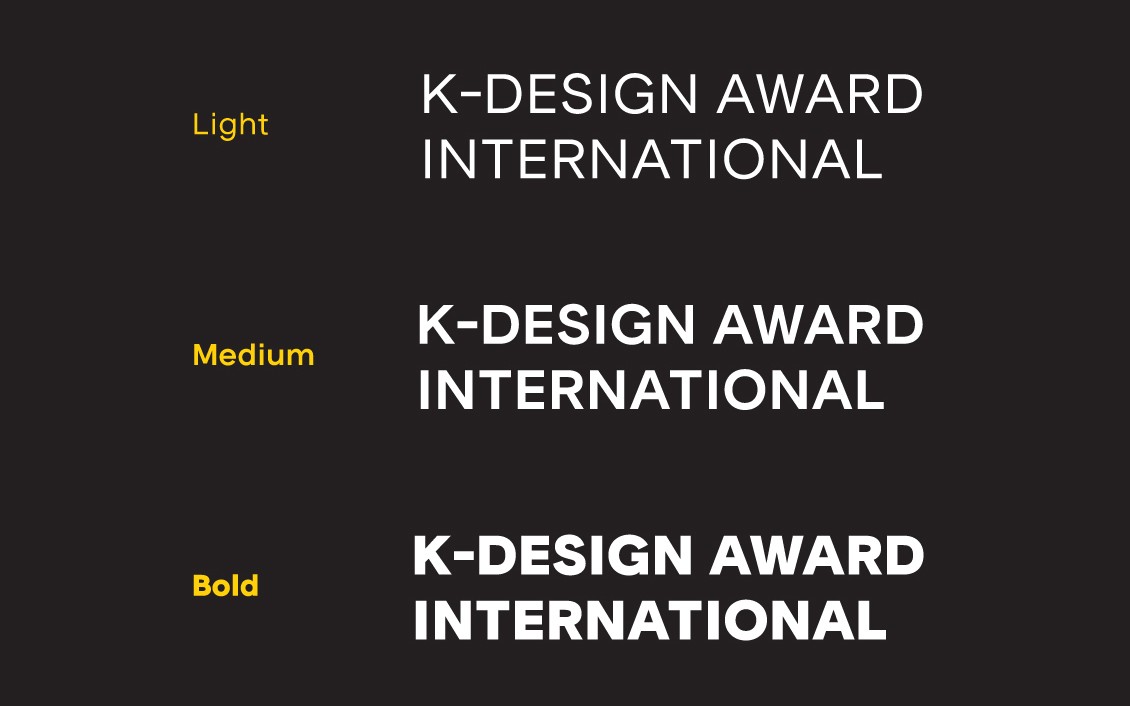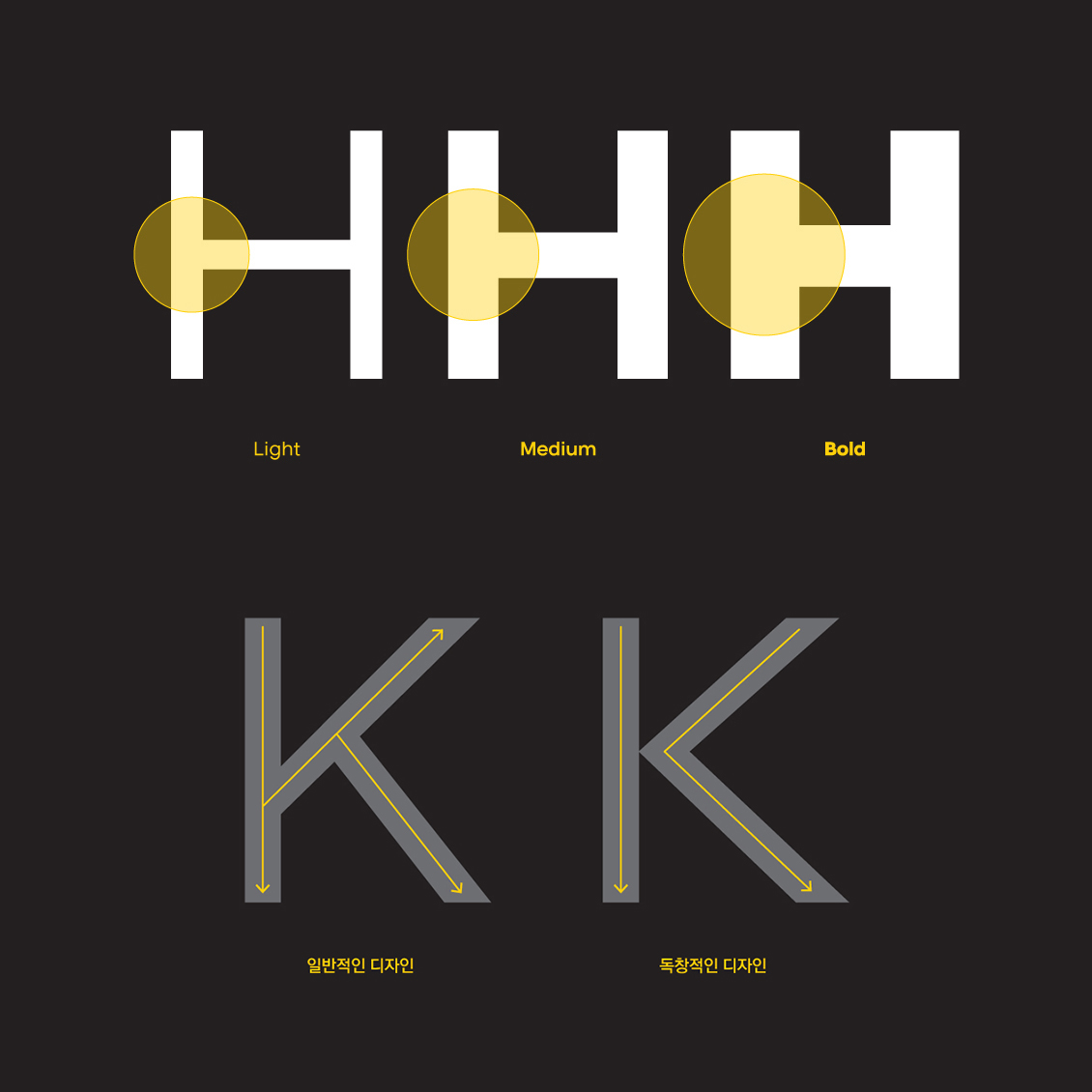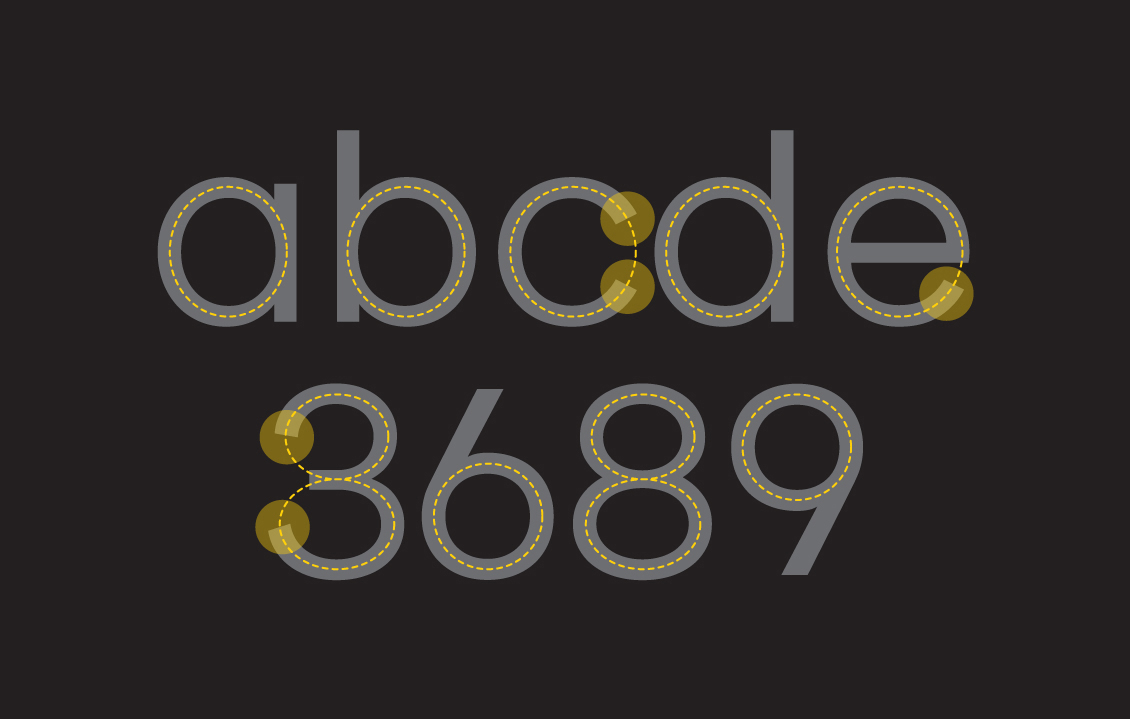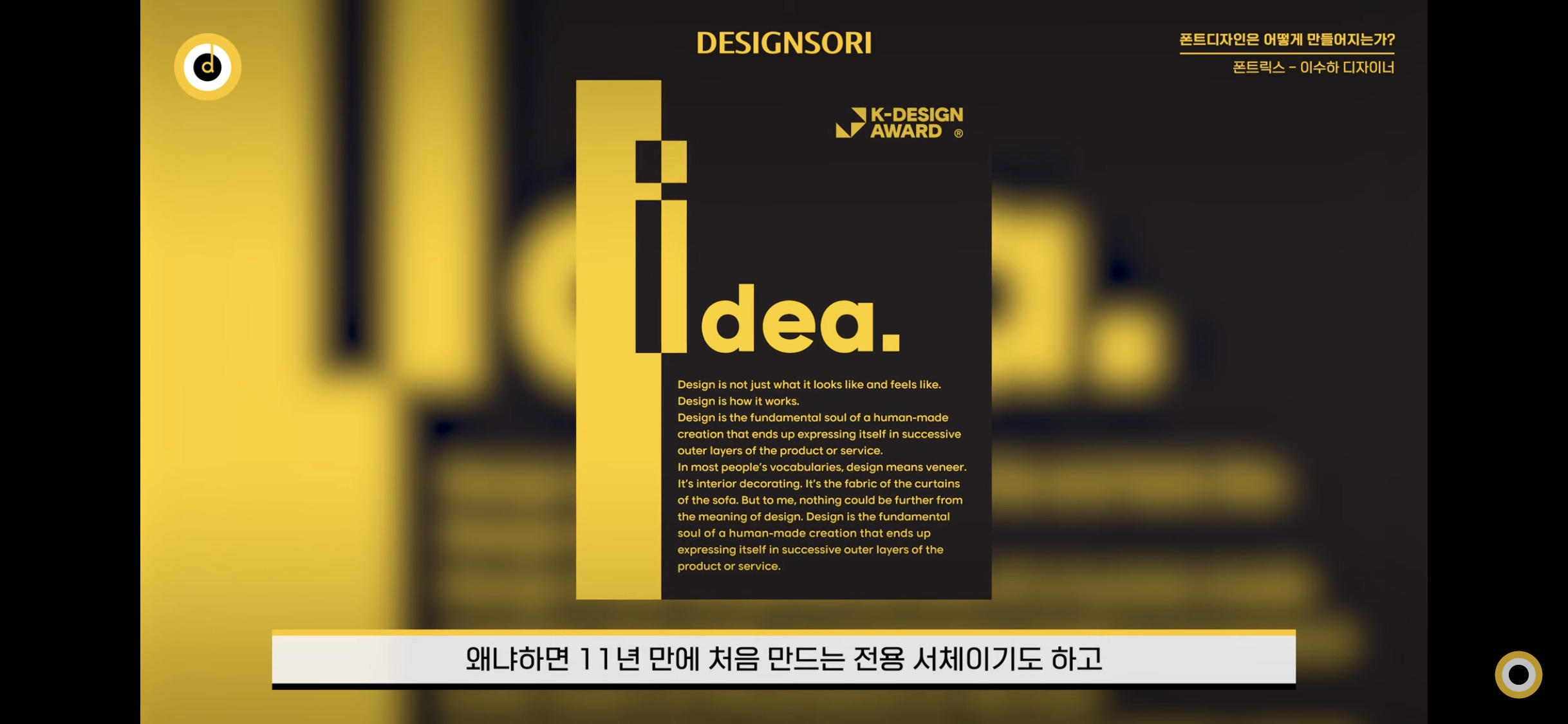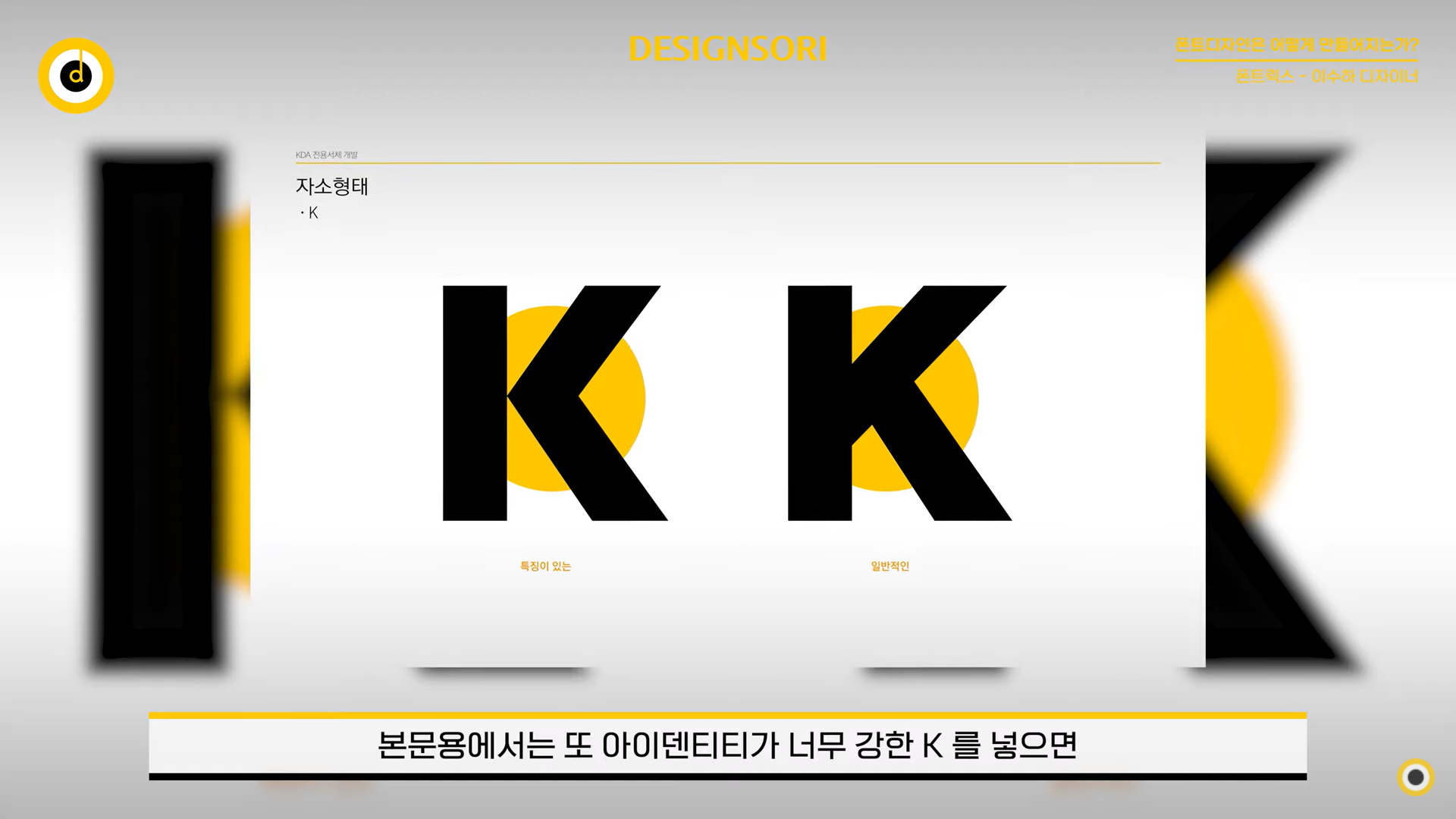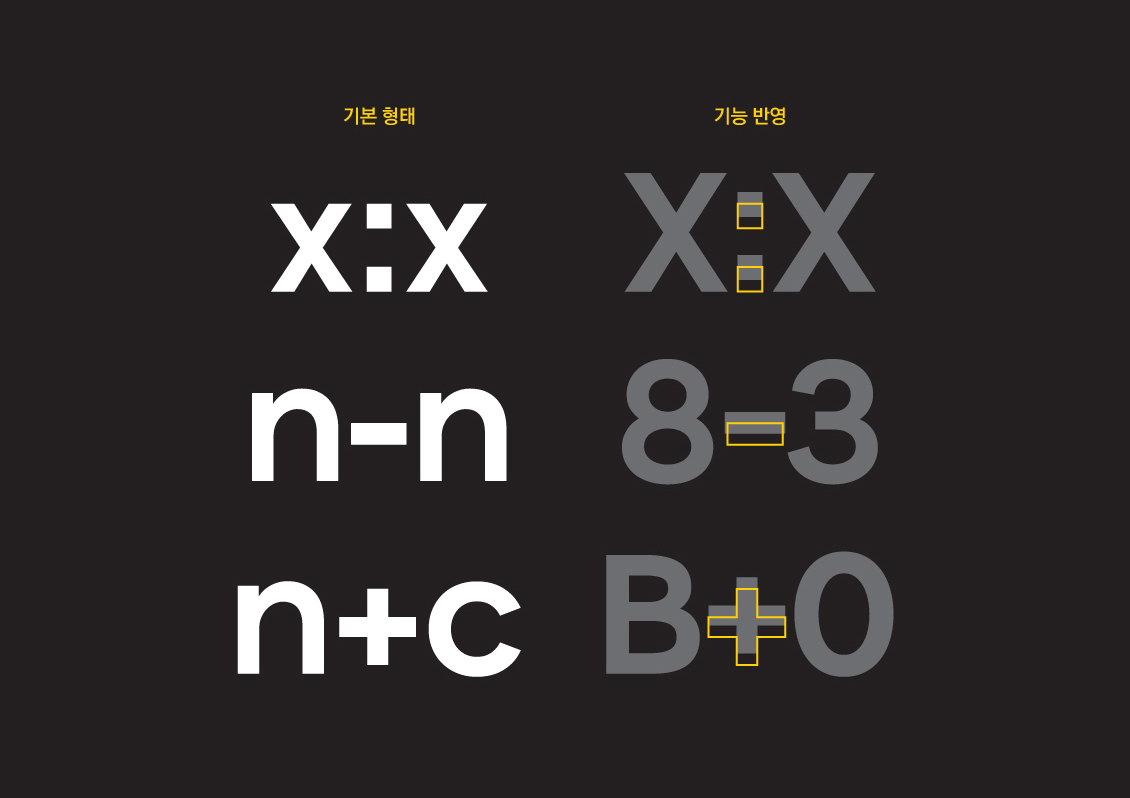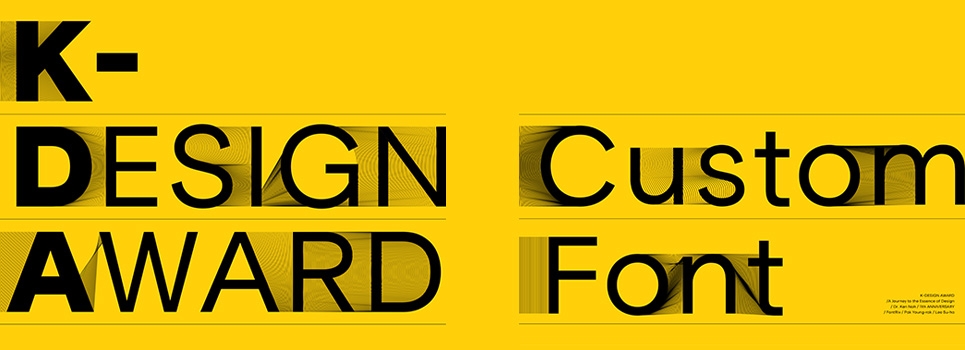
오늘은 아시아 3대 디자인상 중 하나로 세계적인 디자인 공모전으로 발돋움하고 있는 K-디자인 어워드 전용서체로 제작된 「K-DESIGN AWARD」영문 서체를 소개해 드립니다. 주최 11주년을 맞아 역대 모든 수상자를 위해 개발한 서체로, 한국의 디자인 미디어이자 K-디자인 어워드 주최 측인 디자인소리의 의뢰로 전용서체 기획부터 제작까지 함께 진행했습니다. 전문 디자이너를 위한 영문 전용서체로 2022년 5월에 출시된 KDA 전용서체를 만나볼게요.
전문성을 살린 영문 전용서체
이번 K-디자인 어워드 전용서체는 전문 디자이너를 위한 영문 서체입니다. 디자인 어워드 서체이기 때문에 굉장히 감각적이고 디자인적이어야 한다는 생각을 베이스로 디자인을 진행했지만, 오래 사용해도 질리지 않을 베이직함을 갖추려고 했습니다.
기본에 충실한, 그래서 백년이 가도 변하지 않는,
헬베티카 같은 서체를 만들기 위해 노력했다.
박용락 디자이너
KDA 전용서체 디렉팅을 맡은 박용락 이사(디자이너)는 어워드 서체다운 센스와 감각을 겸비하되 베이직한 서체를 만들기 위해 노력했다고 합니다. 그래서 아주 중립적인 편에 속하는 헬베티카 서체와 기하학적 특징이 있는 지오메트릭 산스 서체의 중간 정도로 포지셔닝을 하여 활용도 높은 전용서체를 기획했습니다.
*지오메트릭 산스(Geomatric Sans-serif)
20세기 초 바우하우스 디자이너들의 영향을 받은 기하학적 산 서체는 단순한 기하학적 모양(원, 삼각형, 직사각형)에서 파생된 산세리프 글꼴이다. 최소한의 대비와 고른 너비로 기하학적 서체는 응집력이 있지만 현대적인 느낌을 준다.
아이덴티티가 강한 서체는 당장은 좋을 수 있지만 활용성이나 범용성이 떨어지는 케이스를 다년간의 경험으로 확인했기에, 난이도가 더 높아도 향후에 더 힘을 발휘할 수 있고 완성도와 전문성을 갖춘 기본에 충실한 서체로 개발했습니다.
베이직하고 감각적인 디자인
KDA 전용서체는 활용도를 위해 Light / Medium / Bold 총 3가지 두께로 파생했습니다. 화면에서 작은 글씨로 많은 텍스트가 쓰여 있으면 글씨가 뭉쳐 보이는 경우가 있죠? 디스플레이, 인쇄물, 영상 등 다양한 환경에서 보여지는 영문 서체임을 고려하여, 본문에서 쓰일 때 자간이 적절하고 글자가 뭉쳐 보이지 않도록 두께 파생에 더욱 신경 써서 작업했습니다.
현대적인 이미지를 주는 지오메트릭 스타일의 서체로 각 굵기마다 가로와 세로 획 대비를 균일하게 설정해 안정감을 주었습니다. 또한 기하학적이고 미래지향적인 성격인 로고와의 어우러짐을 고려해, 두 가지 사용이 가능한 K 대소문자 디자인으로 아이덴티티와 사용성 모두 살리도록 제작했습니다.
영문과 숫자에서 정원에 가까운 원형 디자인과 터미널(획의 끝맺음 부분)이 사선으로 깔끔하게 떨어지는 디자인으로 모던함이 돋보입니다. 가독성을 놓치지 않으면서도 디자인적인 특징이 드러나도록 제작했습니다.
글로벌 어워드에 걸맞은 서체
KDA 전용서체 제작을 맡은 폰트릭스 이수하 디자이너는 글로벌 디자인 어워드 서체인 만큼 다른 나라 언어와 함께 사용될 경우가 많은 것을 고려해 중국어, 일본어 등 (Noto Sans) 서체와 혼용하여 사용할 수 있도록 굵기를 맞추는 프로세스를 진행했으며, K-디자인 어워드에서 아이덴티티가 되는 대문자 'K'에는 글립을 추가해 두 가지를 모두 사용하는 방식을 채택했습니다.
전용서체를 제작하면서
사용성과 독창성 둘 다 포기할 수 없었다.
이수하 디자이너
'K'의 글립 디자인 외에도 조건에 따라 대체되는 기호나 부호 글립으로 대문자, 소문자, 숫자에 맞춰 높이가 달라지는 기능을 반영하여 사용성을 높였습니다.
K-Design Award 영문 서체의 활용
앞으로가 더욱 기대되는 K-디자인 어워드 전용서체. 깔끔하고 잘 다듬어진 서체의 디자인이 여러 환경에서 잘 어우러지는 것을 볼 수 있습니다. 로고와의 조화, 아이덴티티, 사용성 모두 욕심을 내어 제작한 서체인 만큼 앞으로 홈페이지나 수상 패키지 등 다양한 곳에서 활용될 것을 생각하니 기대가 됩니다.
KDA 영문 전용서체는 한글을 필두로 한 전용서체 개발에 주로 주력해 온 폰트릭스에게도 한 단계 더 발전하게 된 계기가 아닌가 싶습니다. K-디자인 어워드가 전용서체와 함께 서계로 뻗어나가는 과정을 함께하게 되어 더욱 뜻깊은 마음입니다. 클라이언트와의 많은 커뮤니케이션으로 단순히 기술적으로 뛰어난 폰트를 넘어서 사용자가 원하는 서체와 디자인적인 서체의 균형을 잘 맞추어 제작한 전용서체였기에 완성도가 높았던 사례입니다.